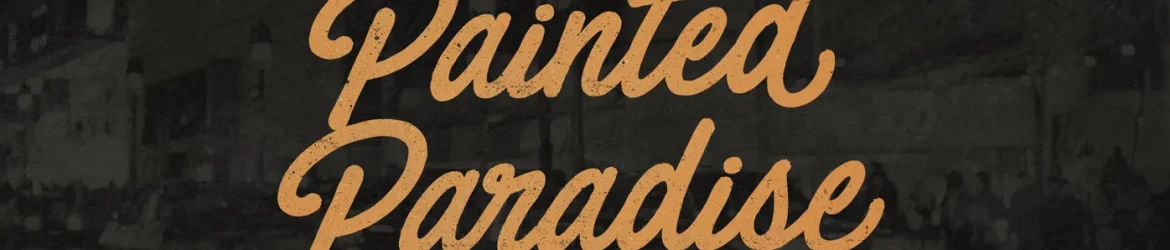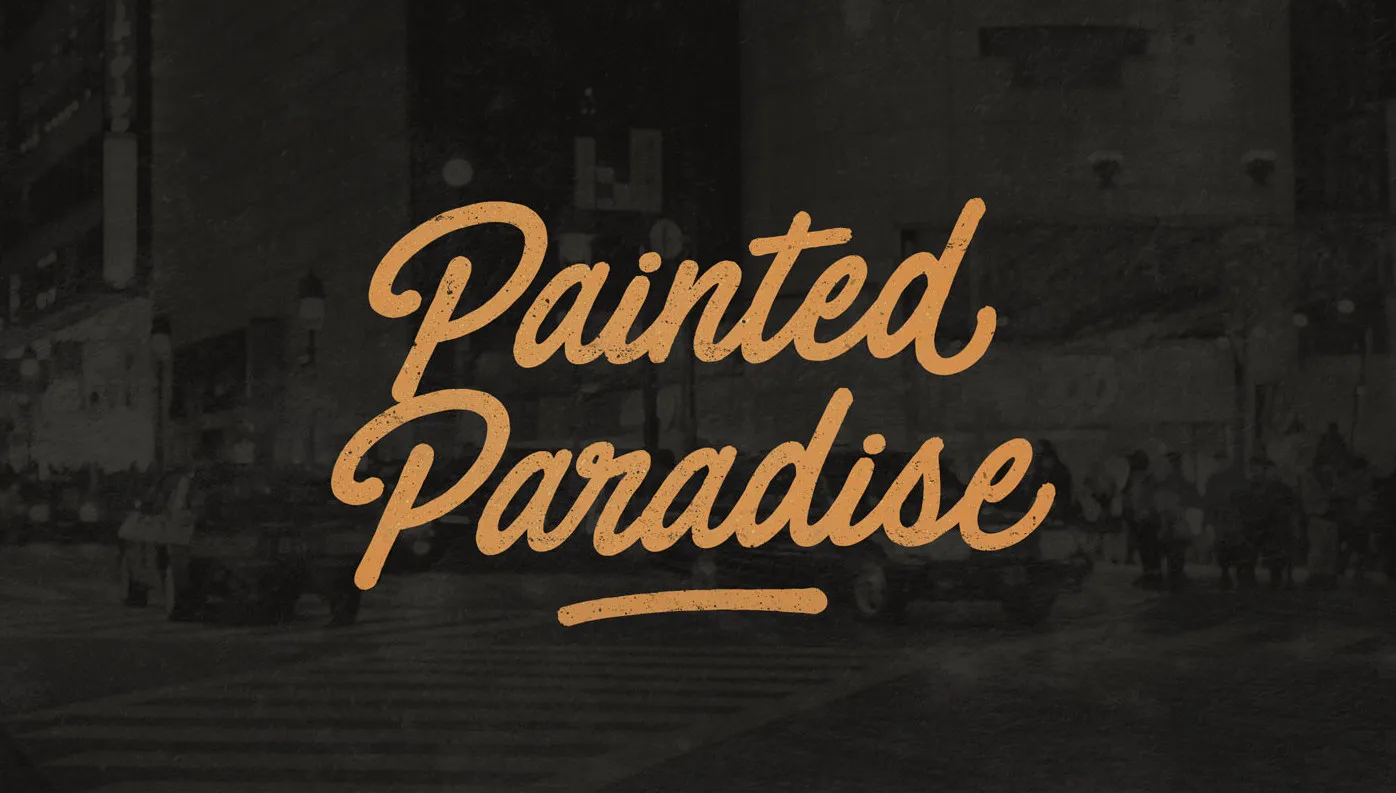
Painted Paradise Font – Fonte Grátis
Painted Paradise Font
A Fonte Painted Paradise foi criada pela 178-MC e é uma mistura única de tipografia rústica com texturas modernas. Inspirada no estilo de desenho à mão livre, esta fonte contemporânea se destaca como um recurso perfeito para designers atentos aos detalhes. Suave e sofisticada ao mesmo tempo, ela traz uma sensação natural e autêntica em qualquer projeto gráfico que seja seu refúgio criativo. Ideal tanto para títulos quanto para aplicações mais elaboradas, a Painted Paradise é ideal para os designers buscando estilos únicos e originais. Suas linhas fluidas e desenhos naturais garantem uma apresentação arrojada em qualquer projeto, seja para uma camisa de desenho animado, um livro ou até mesmo na embalagem de sua próxima linha de cosméticos. Engane-se se pensasse que a Painted Paradise era apenas uma fonte. Ela pode ser o ponto final perfeito para seu próximo projeto visual.